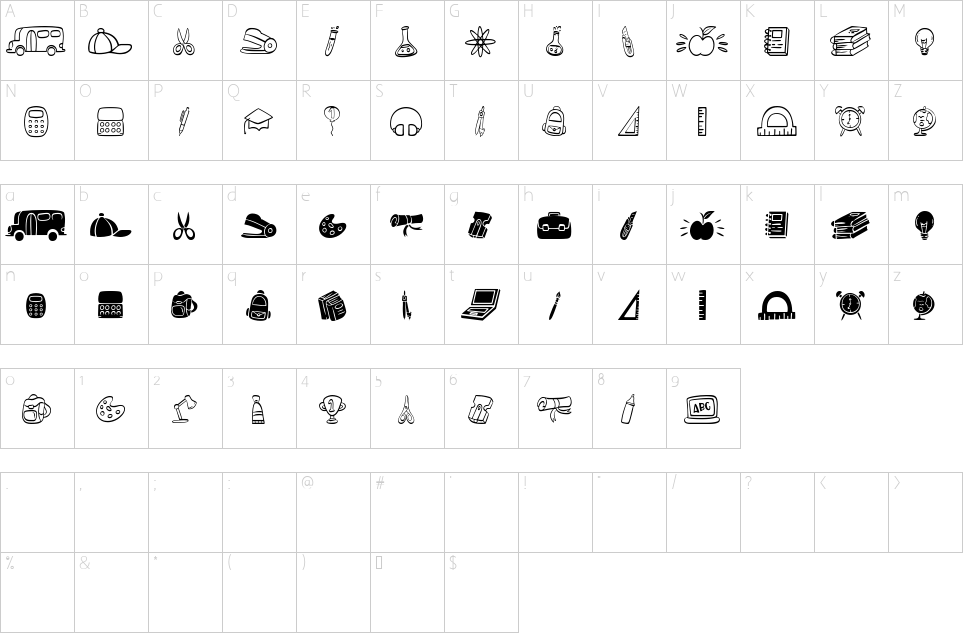
A Dotuku Dingbats é uma elegante fonte gráfica de desenhos que foi criada por Situjuh Nazara. Essa fonte adicionalmente enriquece a composição visual de seus projetos, oferecendo um leque diversificado de símbolos e ícones que são frequentemente usados em design editorial, gráficos de newsletter e até mesmo em designs de websites. Foi descarregada 2.008 vezes desde sua disponibilização, o que mostra seu valor para designers digitais atentos à precisão visual. A Dotuku Dingbats é uma fonte gratuita para Windows e Mac, projetada para complementar qualquer conjunto de fontes existente sem causar sobrecarga na interface do usuário. Com a Dotuku Dingbats, designers podem explorar novas maneiras de estilizar seu trabalho, tornando as páginas e documentos mais interessantes e atraentes. Se você busca uma fonte gráfica que não apenas complementa sua paleta existente, mas também adiciona um toque único e criativo a seus projetos, então Dotuku Dingbats pode ser o que você precisa.